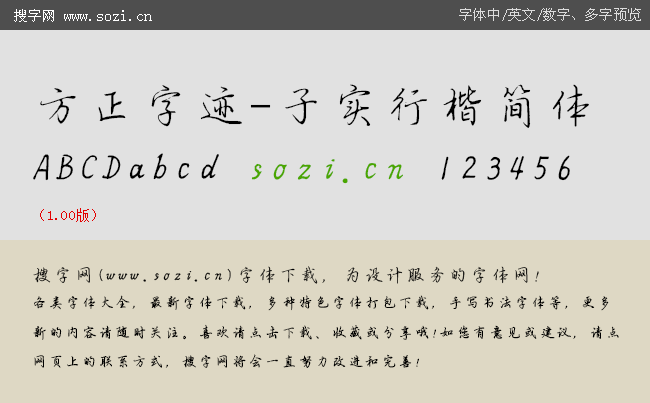
方正字跡-子實(shí)行楷簡(jiǎn)體
搜字網(wǎng)給大家提供一款書(shū)法風(fēng)格的方正字跡-子實(shí)行楷簡(jiǎn)體下載。方正字跡-子實(shí)行楷簡(jiǎn)體是一款硬筆手寫(xiě)字體,由中國(guó)硬筆書(shū)法協(xié)會(huì)會(huì)員楊子實(shí)先生創(chuàng)作。字體規(guī)范流暢,整體協(xié)調(diào),又帶點(diǎn)毛筆筆法,讓屏顯和印刷的字更有書(shū)法美感。適用于報(bào)紙、刊物、電影、電視等環(huán)境。
• 風(fēng)格類別: 手寫(xiě)書(shū)法體